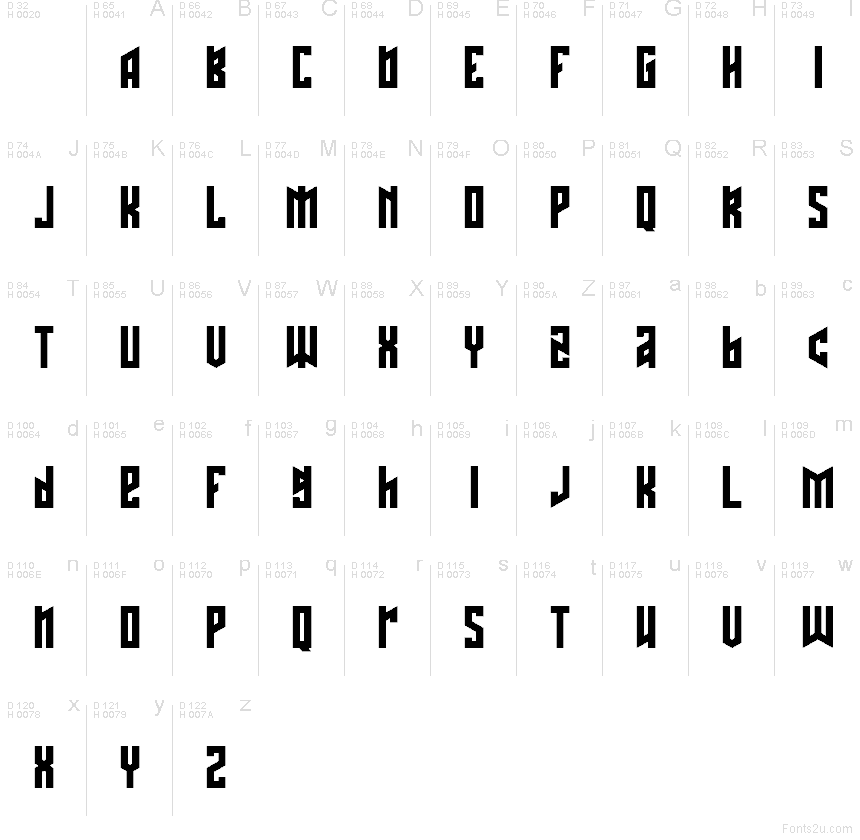
Schwachsinn Labels od Vladimira Nikolice je bezplatné moderní gotické display písmo s nekompromisní industriální siluetou. Jeho vysoké, těsně sázené verzálky využívají přísné svislice, klínovité zářezy a prudké diagonální spoje. Výsledný dojem je hutný a mechanický.
Obalový design skvěle vyhovuje jeho ostře řezanému liternictví, zejména u produktů spojených s metalem, streetwearem nebo extrémními sporty. Hodí se také na koncertní plakáty a herní grafiku postavenou na motivech hrozby či dystopických strojů. V redakčním designu dokáže proměnit titulní záhlaví ve výrazný architektonický prvek.